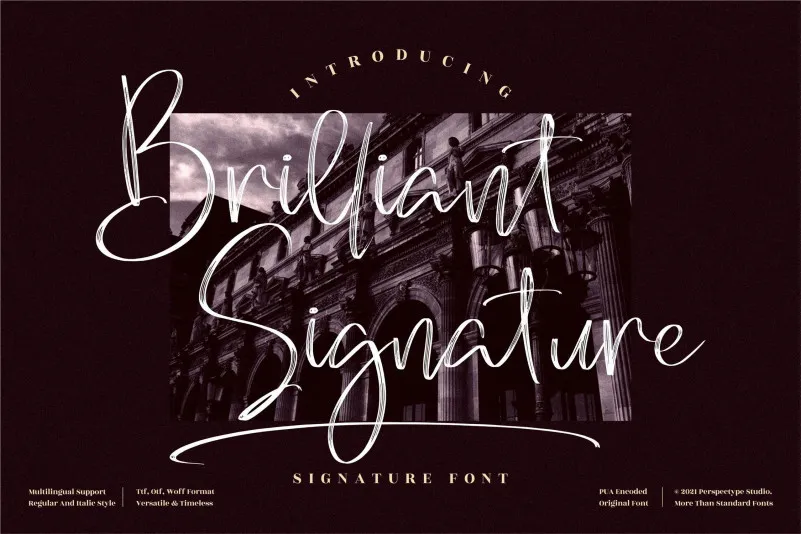
A “Brilliant Signature Font” é uma elegante caligrafia fina e delicada projetada para designers amadores e profissionais. Com seu ar sofisticado e moderno, essa fonte pode ser usada com sucesso em variedades de aplicativos como logomarcas, identidades corporativas, convites, materiais de estação, designs de casamentos e até mesmo posts nas redes sociais. Perfeita para quem busca uma combinação única entre a elegância clássica e um toque moderno na sua criação visual. Esta fonte é o complemento perfeito para qualquer projeto gráfico que deseja ter o seu próprio toque de sofisticação e criatividade. Não importa qual área do design você esteja explorando, a “Brilliant Signature Font” certamente será um recurso invaluable no seu arsenal de ferramentas.